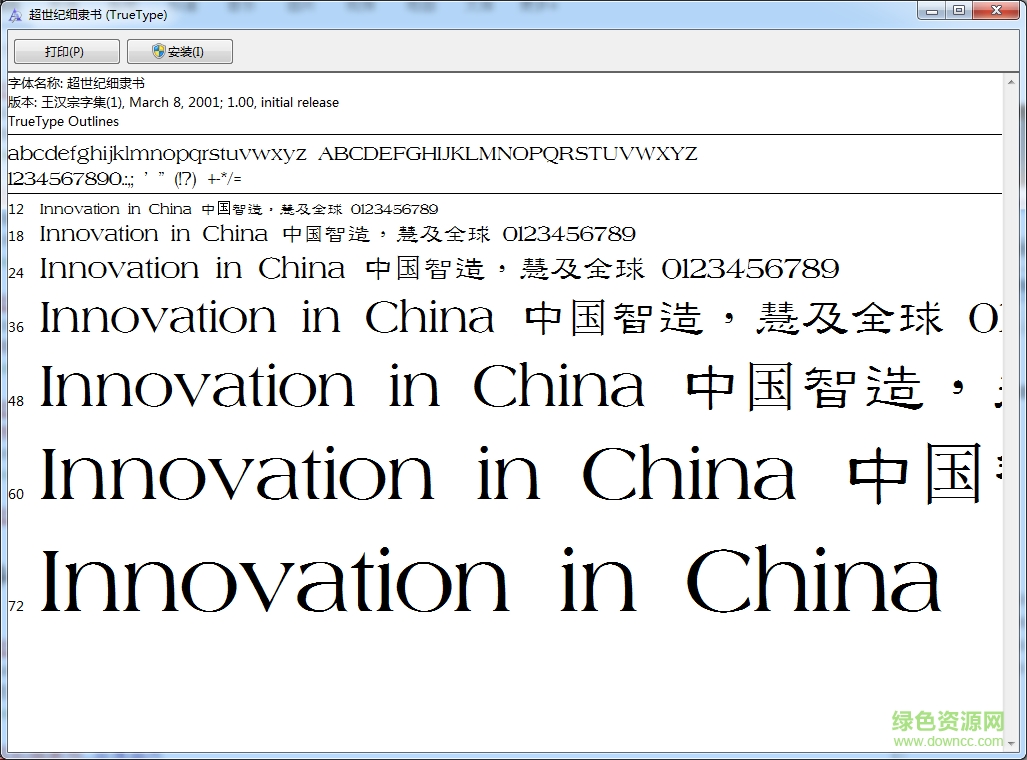
超世紀細隸書是一款以隸書字體為特色的超世紀字體軟件,字體筆畫流暢纖細,整個字體十分的適合打印,打印出來的效果十分的好,而且間隔間距什么也是非常不錯,免費使用非常便捷??靵砭G色資源網(wǎng)下載體驗吧!
超世紀細隸書是一款應用于設計方面的中文簡體漢字,字形精致小巧、標準大方,可廣泛應用于平面設計、廣告設計、報紙雜志、藝術創(chuàng)作等領域,喜歡的網(wǎng)友可免費下載收藏。